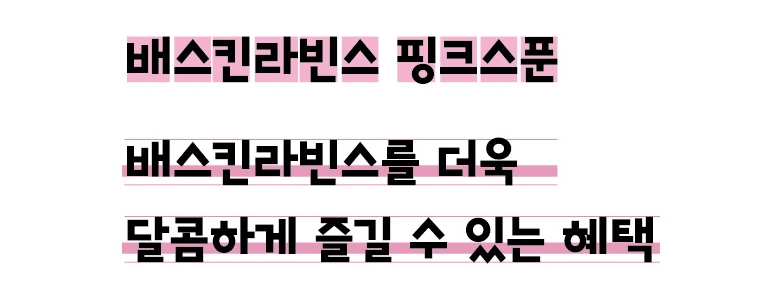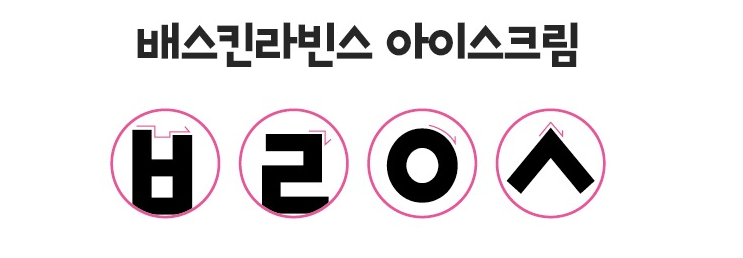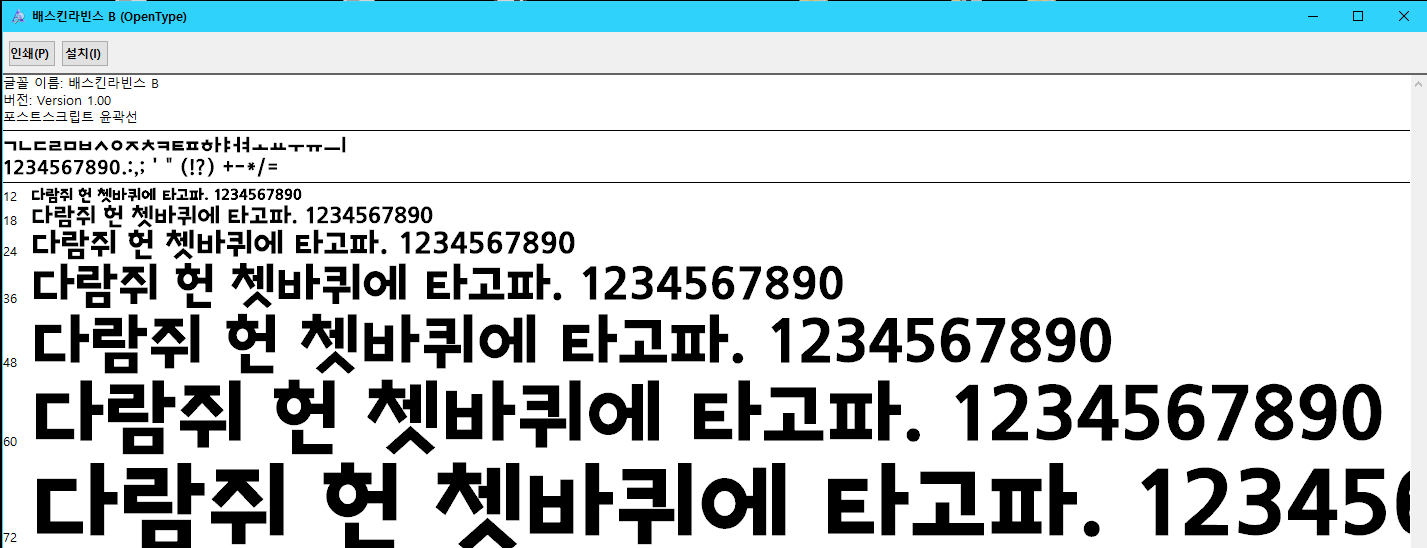
안녕하세요 오늘 소개드릴 상업적 무료 폰트는 베스킨라빈스 폰트입니다. 배스킨 라빈스 폰트는 2018년도 한글날을 기념하기 위해 무료로 배포된 글꼴입니다. 한글 자음 및 모음의 좌우 대칭이 살짝 다른 것이 배스킨라빈스 폰트의 특징인데요.
베스킨라빈스 폰트는 글자마다 특징이 돋보이도록 가변폭을 적용해 글의 흐름이 좋도록 제작되었습니다. 또 베스킨라빈스 폰트 B, 베스킨라빈스 폰트 R로 두 가지 종류의 폰트 버전을 다운로드할 수 있습니다.
초성의 세로획과 가로획의 높낮이 차이로 다양한 아이스크림의 플레이버를 표현하고, 받침도 들쭉날쭉한 형태로 배스킨라빈스 특유의 유쾌하고 통통튀는 귀여움을 표현하려고 했다고 합니다.